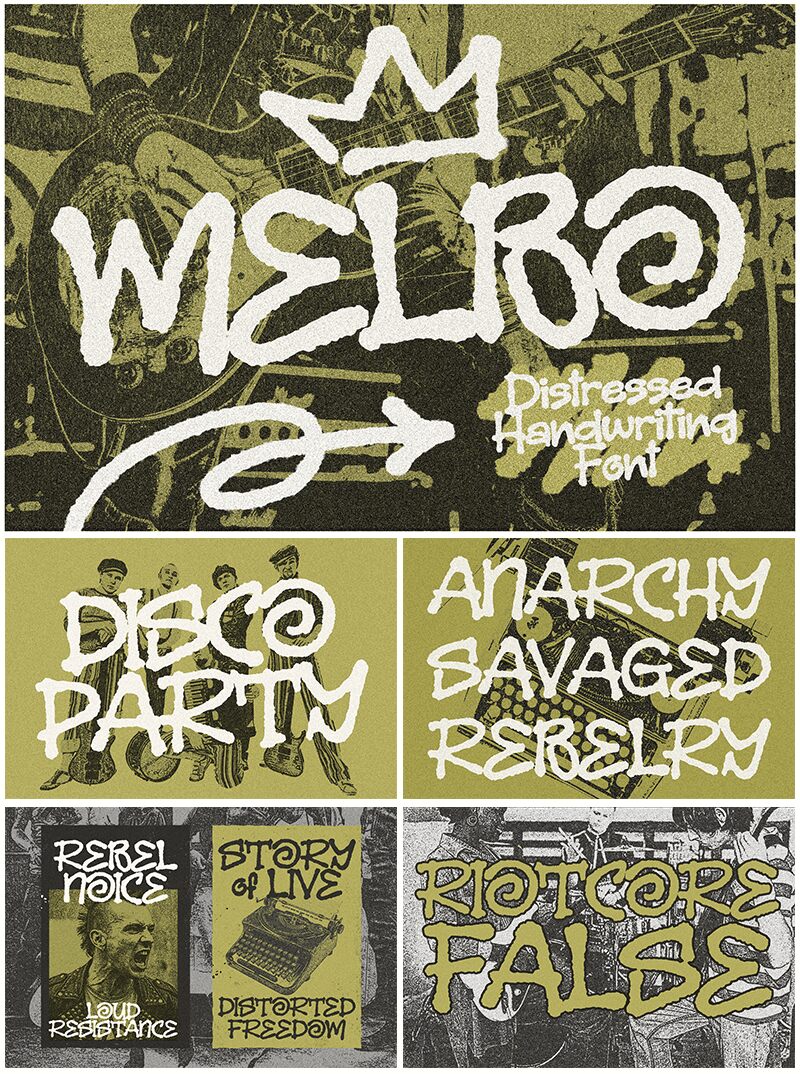
Melbo od Blankids Studio je bezplatné písmo typu brush, formované silnými, ručně malovanými tahy s drsným okrajem, který zůstává u každého písmene přirozeně nepravidelný. Tato rozbitá, inkoustová textura dodává nápisům ležérní malířský rytmus, díky kterému výsledek nepůsobí jako vyhlazená kaligrafie, ale jako spontánní tah štětcem.
E-shopové hlavičky, menu v kavárnách, názvy na plakátech, etikety na obalech i grafika pro sociální sítě – Melbo dává smysl všude tam, kde chcete, aby krátký text působil bezprostředně a ručně vyrobeně. Široké tvary písmen si zachovávají charakter i při rychlém pohledu, zatímco roztřepený povrch pomáhá logům a názvům produktů vyhnout se tomu příliš uhlazenému a umělému vzhledu, který je typický pro mnoho jiných brush fontů.